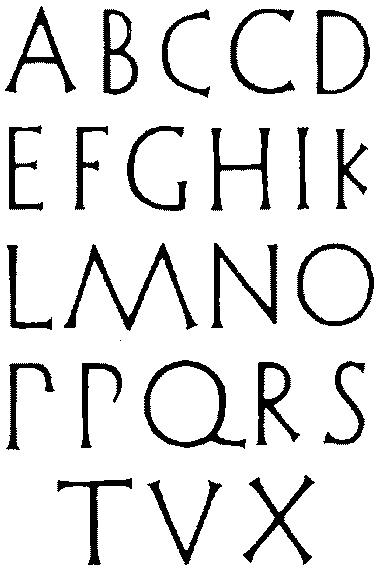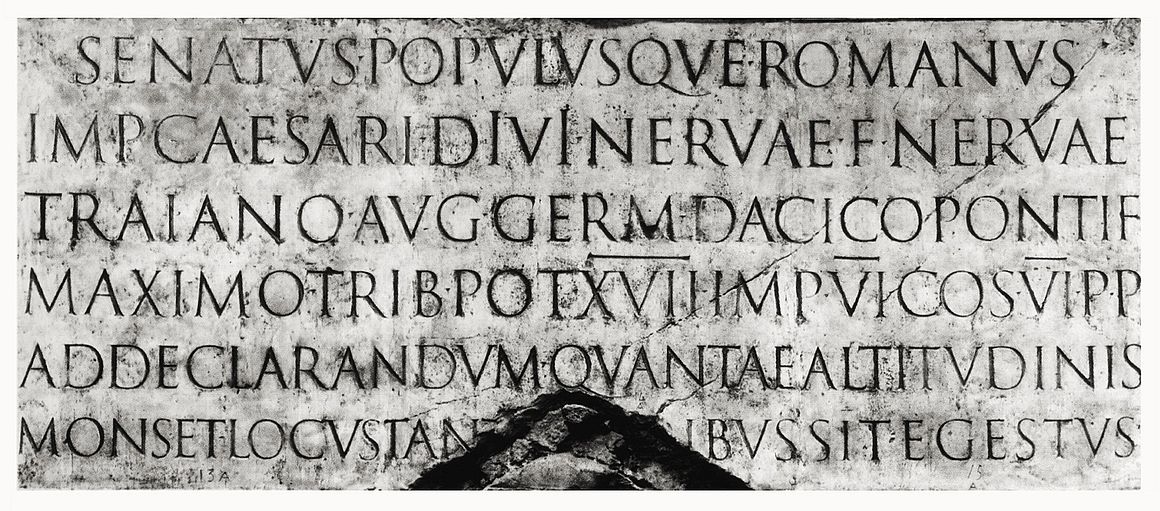
История западной типографики — History of Western typography
Современные типографы рассматривают типографику как ремесло с очень долгой историей, восходящее к первым штампам и штампам, которые использовались для изготовления печатей и валют в древние времена . Базовые элементы типографики, по крайней мере, так же стары, как цивилизация и самые ранние системы письма — ряд ключевых разработок, которые в конечном итоге были объединены в одно систематическое ремесло.
Средневековые корни дизайна
Типографика, создание шрифтов и дизайн шрифтов зародились как тесно связанные ремесла в Европе середины 15-го века с появлением подвижной печати на стыке средневековья и Возрождения . Рукописные формы букв середины 15 века олицетворяли 3000-летнюю эволюцию буквенного дизайна и были естественными моделями букв в систематизированной типографике. Переписчик письмо известное как TEXTUR или textualis , произведенное сильный готический дух Blackletter из рук немецких книжников области, служило в качестве модели для первых типов текста.
Йоханнес Гутенберг нанял писца Петера Шёффера, чтобы помочь разработать и вырезать высечки для первого шрифта — типа DK, состоящего из 202 символов, который использовался для печати первых печатных книг в Европе. Второй шрифт примерно из 300 знаков, предназначенный для 42-строчной Библии c. 1455 год, вероятно, был огранен ювелиром Гансом Данном с помощью двух других — Гетца фон Шлеттштадта и Ганса фон Шпейера .
Культурные традиции гарантировали, что немецкая типографика и дизайн шрифтов оставались верными духу готики / блэклеттера; но параллельное влияние гуманистической и неоклассической типографики в Италии (второй стране, где была сделана печать с подвижным шрифтом) стимулировало textur в четыре дополнительных подстиля, которые были отличными, структурно богатыми и очень дисциплинированными: Bastarda , fraktur , rotunda и Швабахер .
Быстрое распространение подвижной печати по Европе привело к появлению дополнительных готических, полуготических и переходных типов от готики к римской.
Первыми печатниками Испании были немцы, которые начали с печати современных римских шрифтов, но вскоре отказались от них и приняли готические шрифты, основанные на формах букв испанских рукописей. Валенсия в Королевстве Арагон была местом расположения первой печатной машины, основанной в 1473 году. Оттуда печатники переехали в другие города для установки печатных машин. Римские шрифты использовались печатниками Саламанки для своих изданий классических авторов. Печать на португальском языке началась в Лиссабоне в 1495 году (первой книгой, напечатанной в Португалии, была книга на иврите, напечатанная в 1489 году).
Классическое возрождение
В Италии тяжелые готические стили вскоре были вытеснены венецианскими или «старыми» латинскими типами, также называемыми антиква . В inscriptional капители на римских зданий и памятников были структурированы по евклидовой геометрической схеме и дискретной компонентной модели из классической архитектуры . Их структурно совершенный дизайн, почти идеальное исполнение в камне, сбалансированное угловое подчеркивание, контрастирующие толстые и тонкие мазки и вырезанные засечки стали типографским идеалом для западной цивилизации . Самый известный пример римских капителей с надписью существует на основании колонны Траяна с надписью ок. 113.
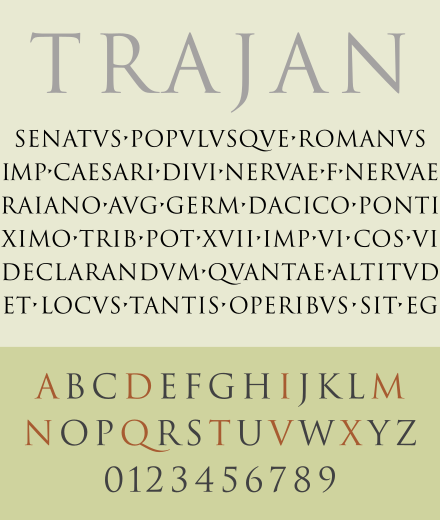
Заметив стилистическое несоответствие между этими двумя очень разными буквами, переписчики изменили дизайн маленькой буквы Каролингов, удлинив восходящие и нисходящие элементы и добавив надрезанные засечки и завершающие штрихи, чтобы объединить их с римскими заглавными буквами. К тому времени, когда подвижный шрифт достиг Италии несколько десятилетий спустя, гуманистическое письмо превратилось в последовательную модель, известную как гуманистический минускул , которая послужила основой для стиля шрифта, который мы сегодня знаем как венецианский.
Переход от гуманистического миниатюрного к римскому типу
Классически богатый город Рим привлек первых типографов, которые, как известно, открыли свои магазины за пределами Германии, Арнольда Паннарца и Конрада Свейнхейма , за которыми следовали братья Иоганн и Венделин Шпейер (де Спира) и француз Николя Дженсон . Последовательность появления и даты производства для типов, используемых этими принтерами, еще предстоит установить; Известно, что все четыре печатали шрифтами от текстурной готики до полностью развитых римлян, вдохновленных ранним гуманистическим письмом, и в течение нескольких лет центр печати в Италии переместился из Рима в Венецию .
Незадолго до 1472 года в Венеции Иоганн и Венделин выпустили материал, напечатанный наполовину готическим-наполовину римским шрифтом, известный как «Gotico-antiqua». Этот дизайн сочетал упрощенные готические капители с рационализированным гуманистическим набором крошечных букв, который сам сочетал готические крошечные формы с элементами каролингов, в одном шаге вперед, на полшага назад в смешении стилей.
Примерно в то же время (1468 г.) в Риме Паннарц и Свейнхейм использовали другой шрифт, очень имитирующий гуманистический минускул, известный как «Лактанций». В отличие от жестких ломаных форм полуготики Шпейера, Lactantius характеризуется плавными буквами с сдержанной органической отделкой. Lactantius a отошел как от каролингской, так и от готической моделей; вертикальная задняя часть и прямоугольная верхняя часть заменили диагональную каролингскую структуру, а непрерывный изогнутый ход заменил сломанный элемент готической чаши.